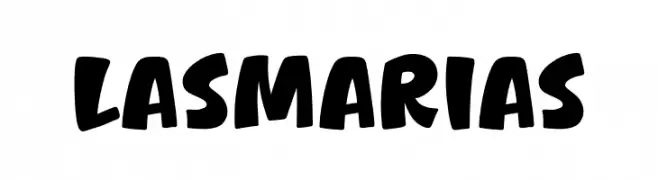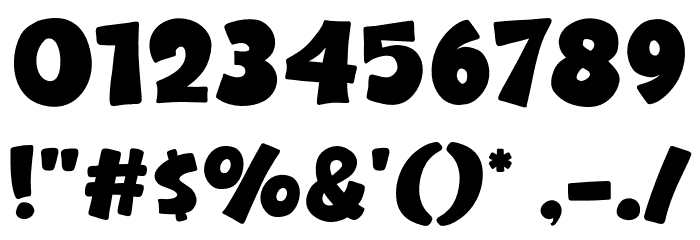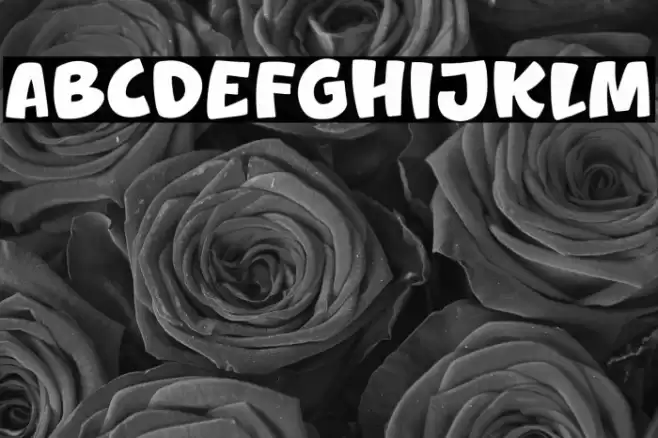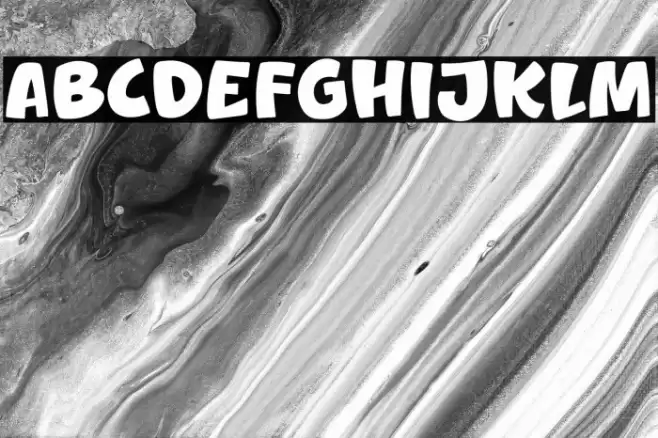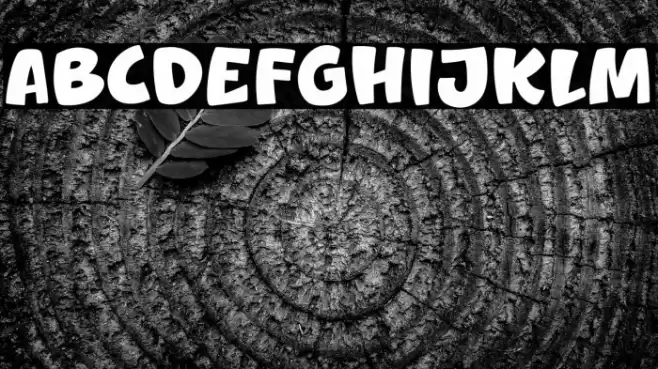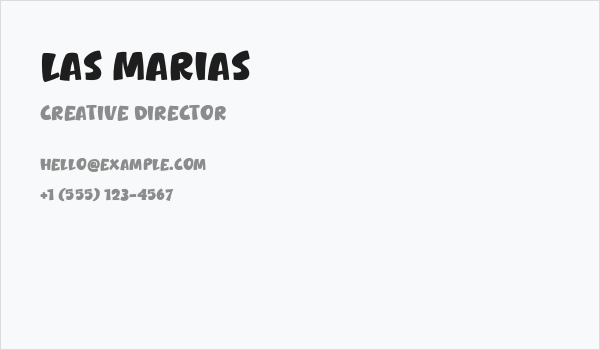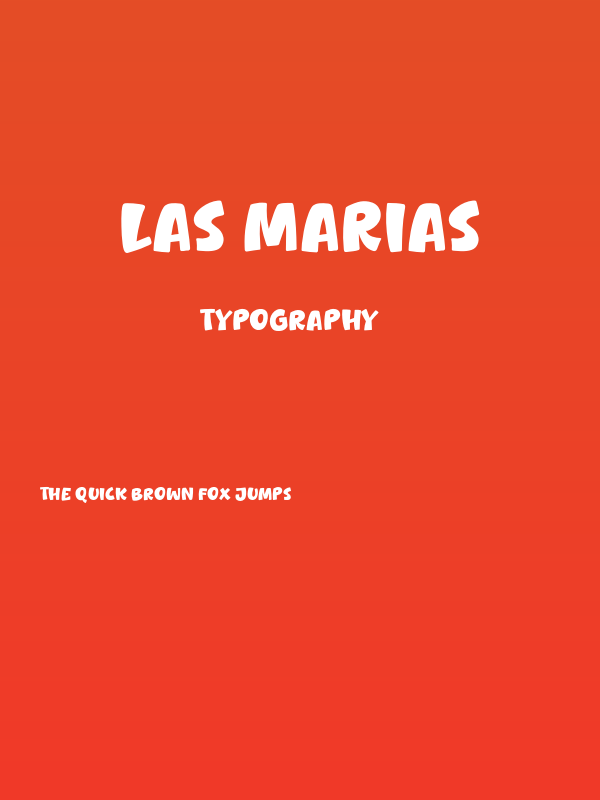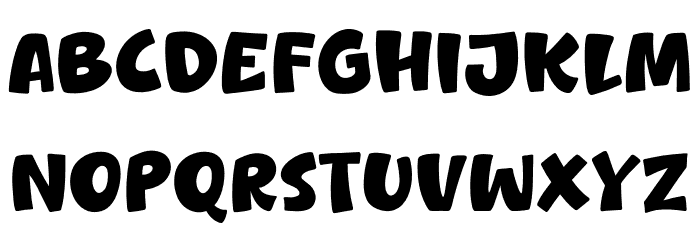
Las Marias Font
| Gesamtstil | Playful, Whimsical |
| Vorgeschlagene Projekte | Ideal for children's books, comic strips, playful branding, and event posters. |